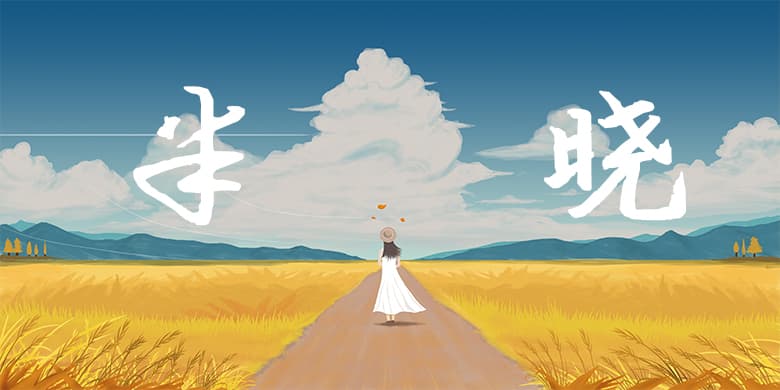
品牌:方正手迹设计师:方正手迹发行时间:2020字库编码:大陆简体(GB2312-80)分类:常规书写·硬笔字体属性:精品字
该字在字形结构上,比较接近启体,结体严谨。但在笔画上,采用较为均匀的粗,在读者视觉感受上,会更加舒适。 适用于文艺类的书刊、品牌广告和产品包装设计,以及社交网络的个性化用字。